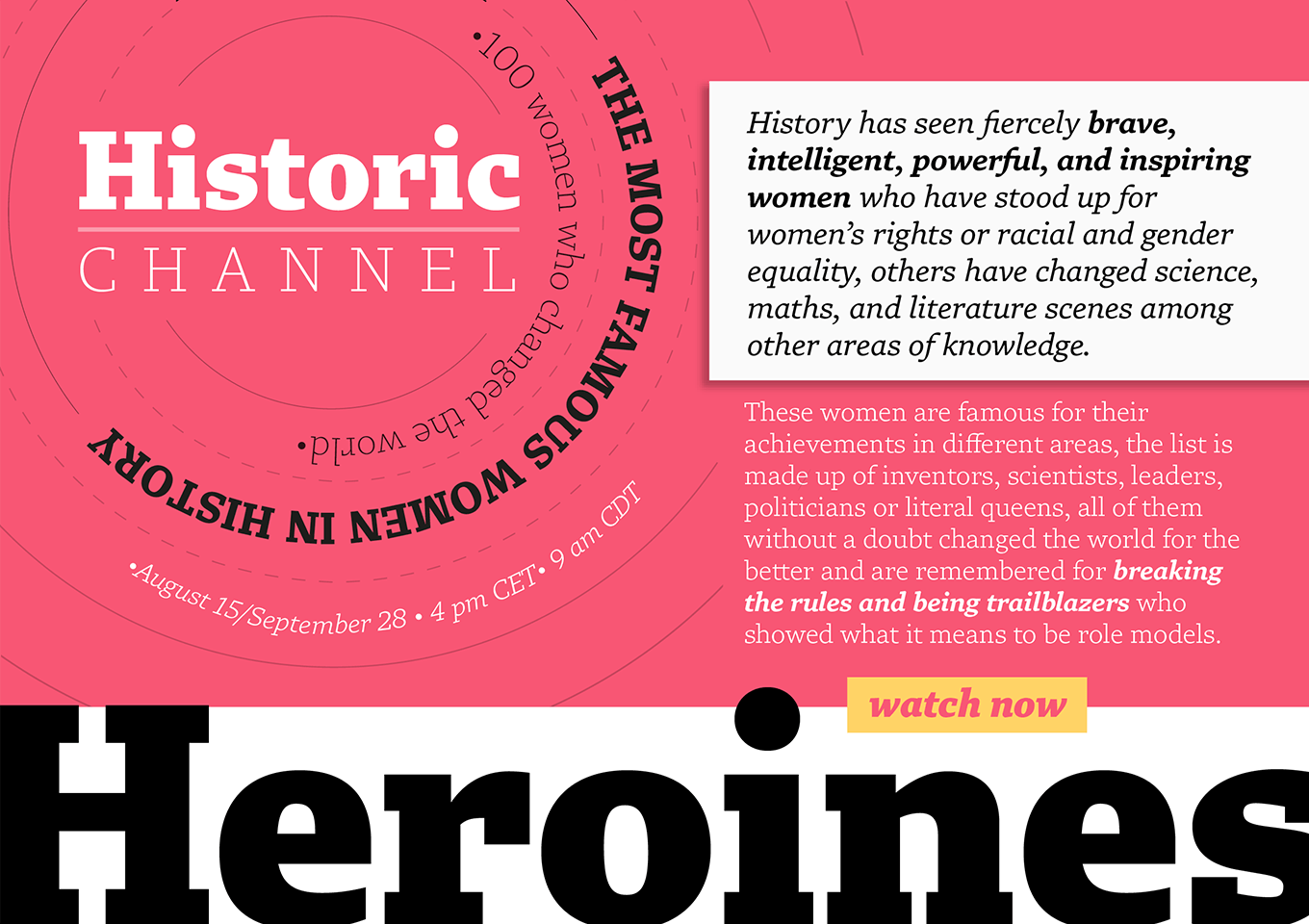
Roleは 、セリフ、サンセリフ、スラブセリフ、ソフト(ラウンデッド)の4つのスタイルと、Text(本文用)、Display(小見出し用)、Banner(大見出し用)の3つのサイズ別に最適化されたバリエーションを持つ、合計200書体のスーパーファミリー書体です。すべての書体は、「誠実さ」と「安定感」をコアイメージとし、Slab は「力強さ」をテーマに制作されています。 Role Slab Textは可読性が高く骨太な印象の本文用書体です。